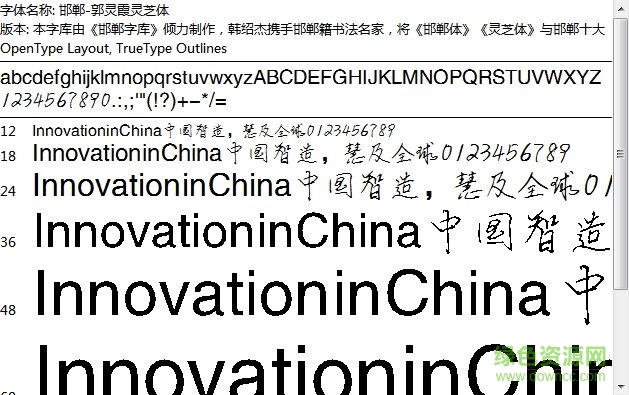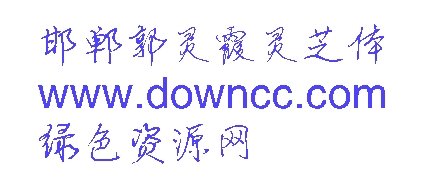
邯鄲郭靈霞靈芝體
邯鄲靈芝體是一款毛筆書(shū)法韻味的手寫(xiě)字體,運(yùn)筆流暢而清悠,筆畫(huà)邊緣似鋸齒,但微小不突出,給文字增加了一股運(yùn)動(dòng)氣息,古樸隨和,喜歡的朋友就來(lái)綠色資源網(wǎng)免費(fèi)下載吧!
邯鄲郭靈霞靈芝體介紹
字體簡(jiǎn)介邯鄲郭靈霞靈芝體字體由邯鄲字庫(kù)傾力制作,韓紹杰攜手邯鄲籍書(shū)法名家,將邯鄲體,靈芝體與邯鄲十大文化和豐富的文化遺產(chǎn)及濃厚的人文精神與推向全國(guó)和世界文化領(lǐng)域。
作者介紹
郭靈霞,女、1966年6月生于文化名城邯鄲,任河北省邯鄲市叢臺(tái)區(qū)五里鋪小學(xué)語(yǔ)文高級(jí)教師,一生致力于《寓古詩(shī)詞誦讀于硬筆書(shū)法中》課題研究,其書(shū)法作品多次在市級(jí)、區(qū)級(jí)比賽中榮獲大獎(jiǎng)。在叢臺(tái)區(qū)文教系統(tǒng)“三字一畫(huà)”基本功大賽中獲四個(gè)一等獎(jiǎng),綜合排名第一名。
字體背景